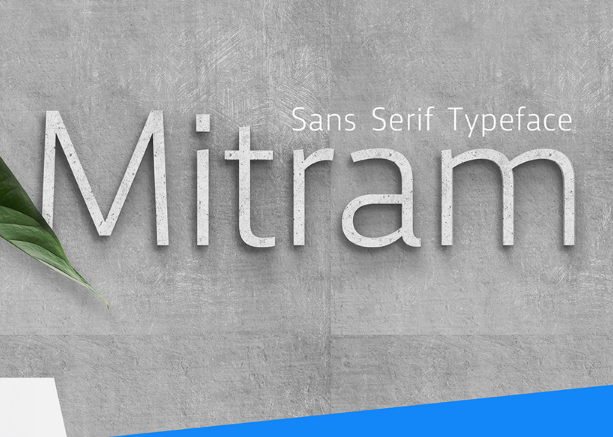
Mitram Typeface – Fonte Grátis
Mitram Typeface
A Mitram Typeface é uma família serifada cuidadosamente projetada por João Symington, oferecendo 7 pesos diferentes – desde Thin até ExtraBold, incluindo itálico para proporcionar uma ampla gama de opções a designers e criativos. Introduzida no mercado de fontes, esta família é desenvolvida especificamente para atender às necessidades dos setores mais variados, como o marketing e embalagens, textos em livros e identidade visual, bem como para aplicações web e digitalização. Suas linhas finas e detalhes elaborados a tornam um recurso inestimável para criação de design, seja ela para texto pequeno ou grandes visuais publicitárias. A Mitram é perfeita para aqueles que buscam uma fonte serifada de qualidade profissional para seus projetos digitais e impressos. Com seu amplo range de opções no peso da fonte, a Mitram oferece aos designers a oportunidade de encontrar o certo match entre sua identidade visual e suas necessidades específicas do projeto.